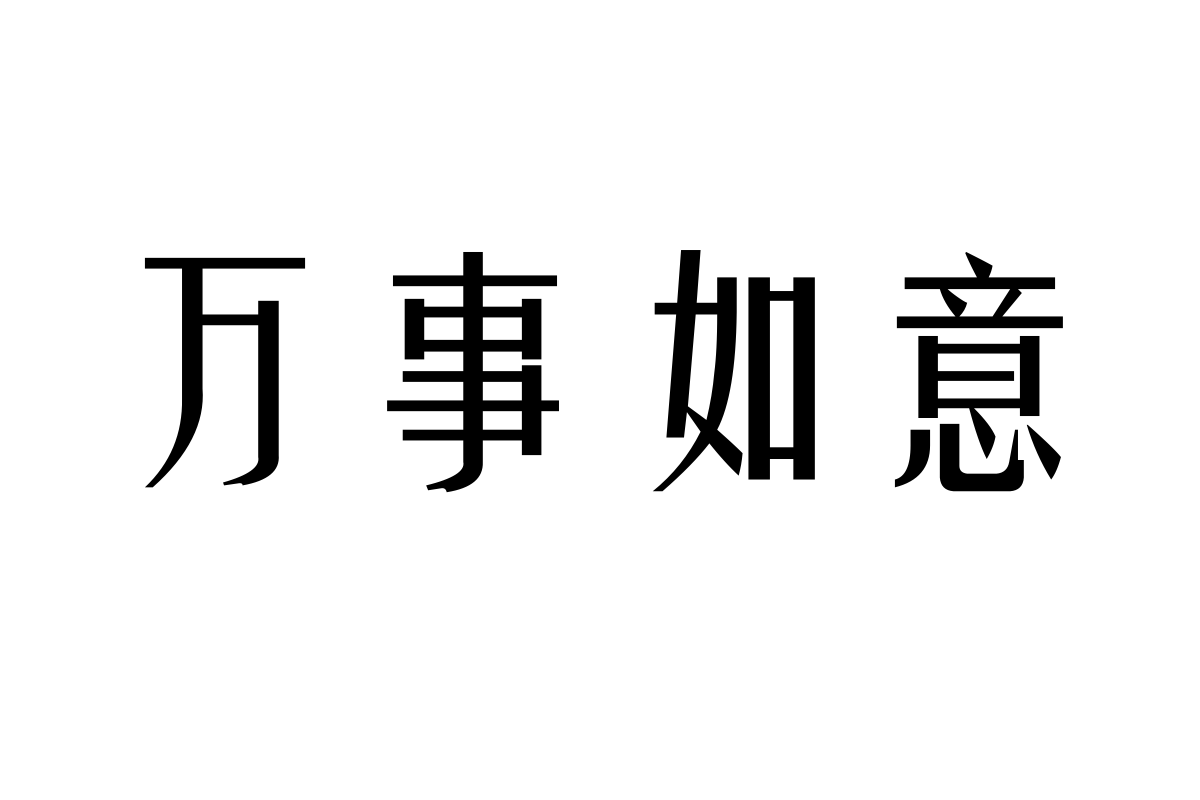
迷你简姚体是一种中文字体,由设计师姚远于2007年设计。这款字体以其简约、现代的风格而受到许多设计师和用户的喜爱。
迷你简姚体的特点是:
1. 字形简洁:这款字体的字形线条流畅,没有过多的装饰,给人一种简洁的感觉。
2. 易于识别:由于其简洁的字形,使得它在印刷品、网页、广告等场合都有很好的识别度。
3. 适应性强:无论是在正式的文件还是非正式的社交媒体上,迷你简姚体都能适应各种场景。
4. 可定制性强:虽然是一款免费字体,但设计师可以根据需要进行一定程度的定制,以满足不同的设计和商业需求。
总的来说,迷你简姚体是一款非常适合现代设计风格的字体,无论是用于印刷品、网页还是广告,都能展现出其独特的魅力。